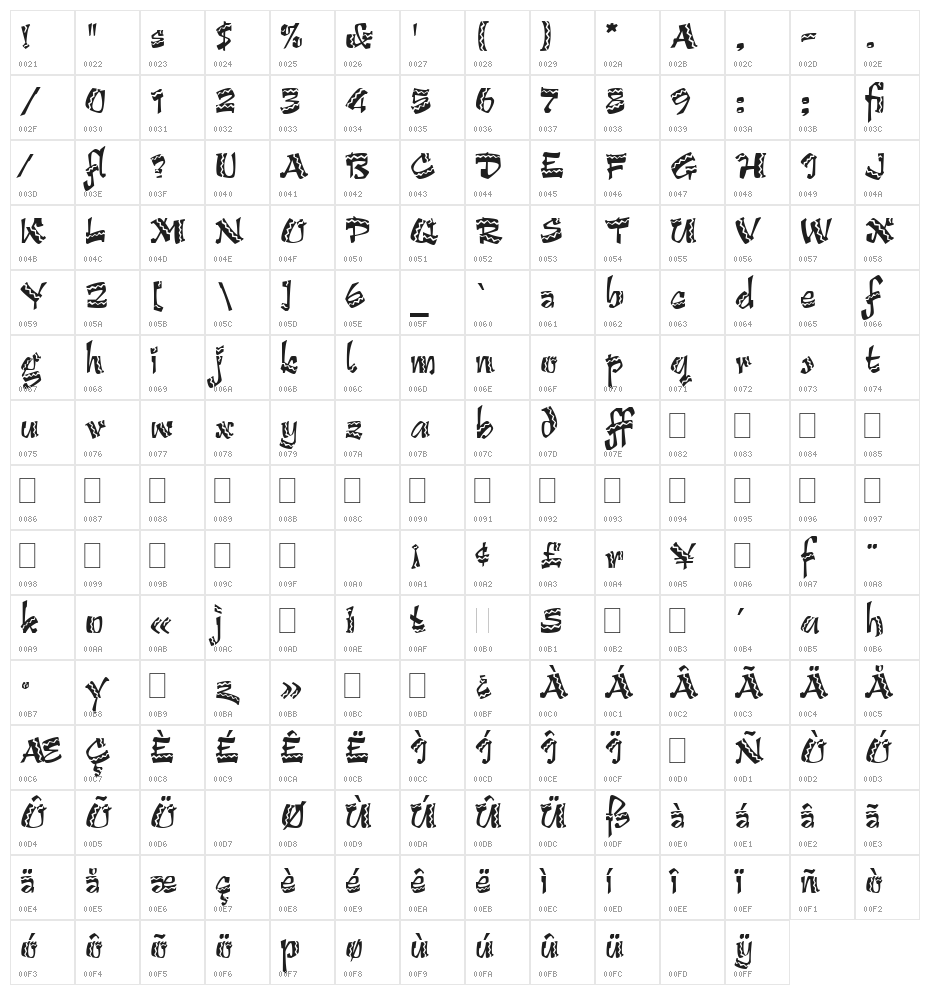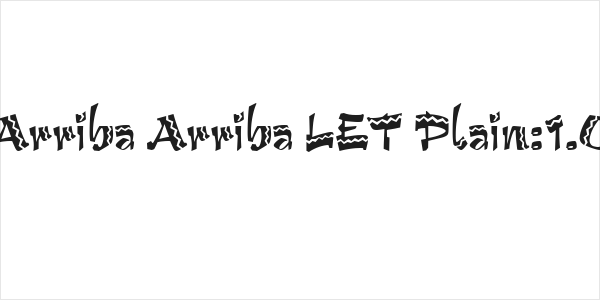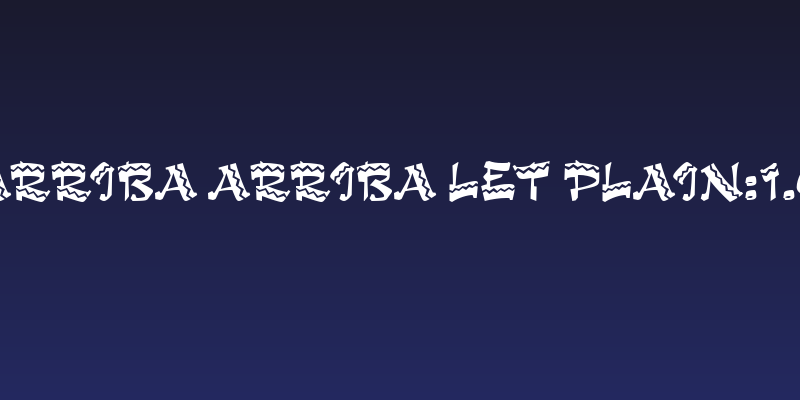
Arriba Arriba LET Plain:1.0 Font
| Progetti proposti | Ideal for posters, event flyers, children's book covers, and any design needing a lively and distinctive typeface. |